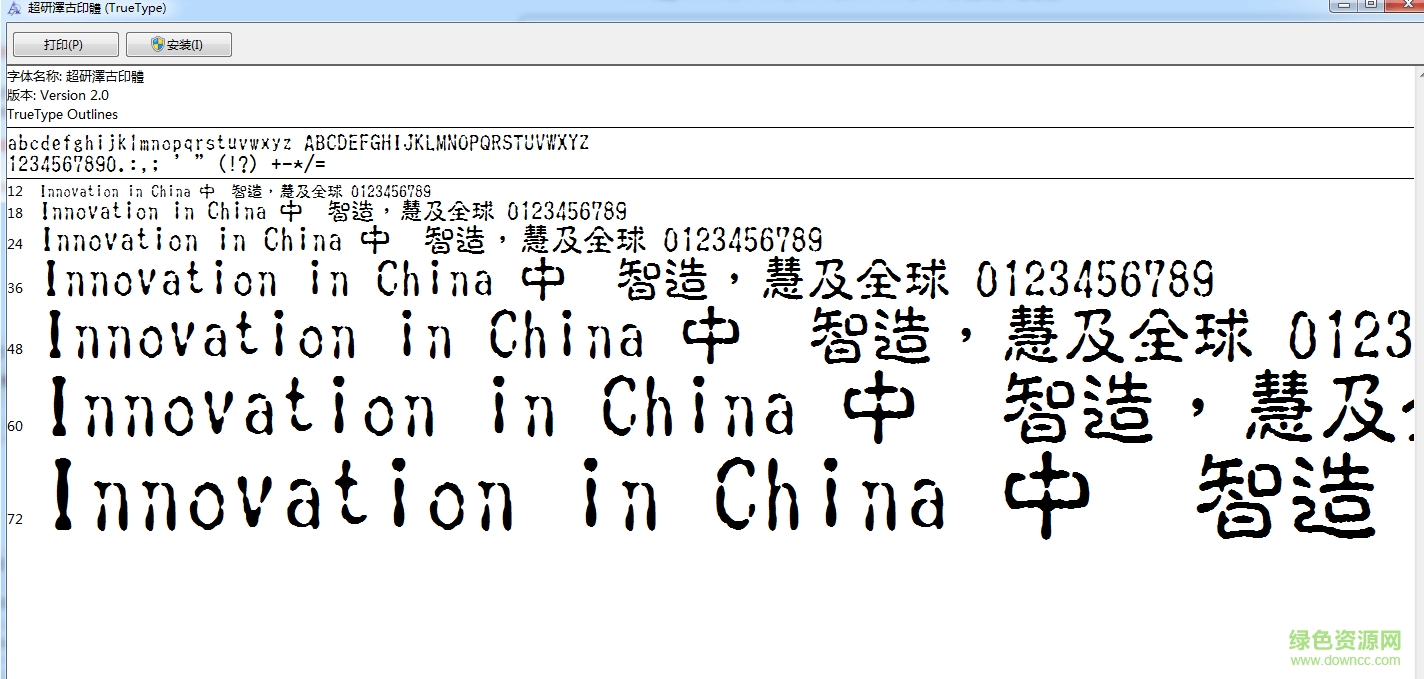
超研澤古印體繁體是超研澤系類的古印體字體,字體采用了繁體為基礎(chǔ)制作而成,也是在古印體中非常具有人氣的字體,本站免費(fèi)的為您推薦下載資源,歡迎您的下載體驗(yàn),無需任何積分即可擁有,需要的用戶快到綠色資源網(wǎng)下載體驗(yàn)吧
超研澤古印體繁體的整個個效果就給人一種古代印章上的效果,雖然它的橫豎不是特別的筆直,但是卻個人一種別樣的風(fēng)采